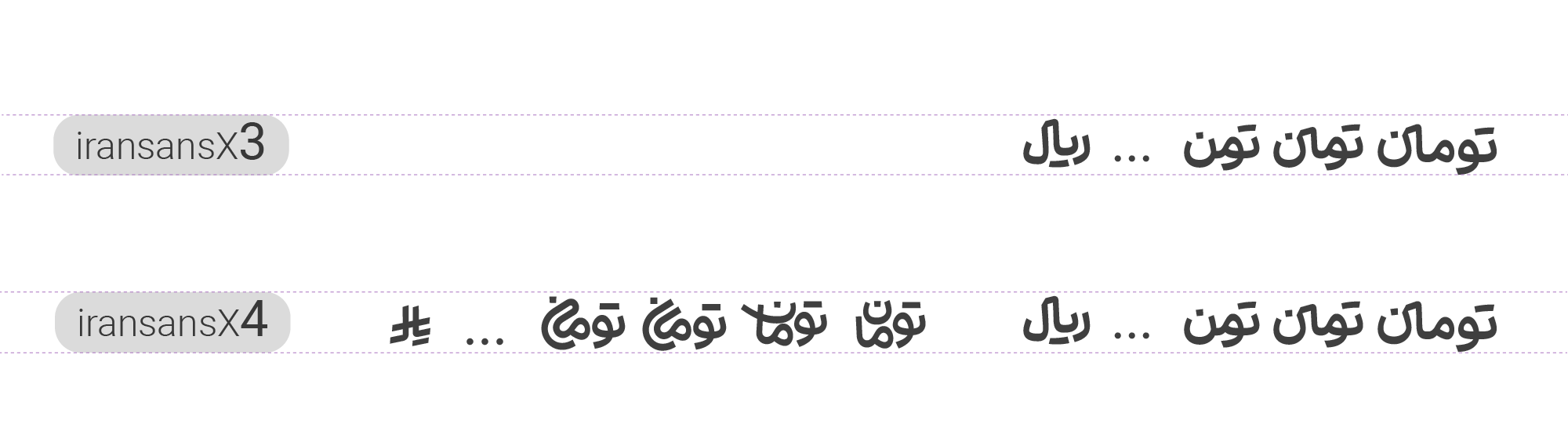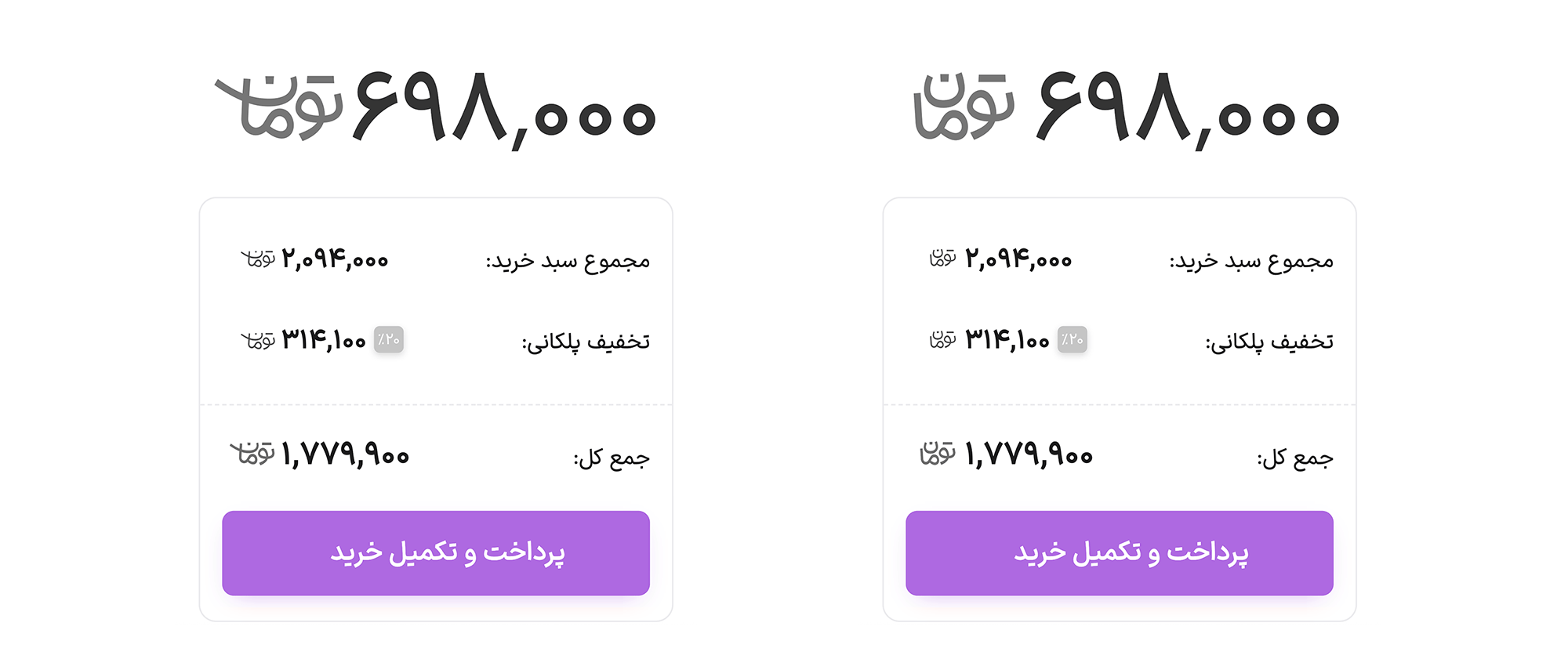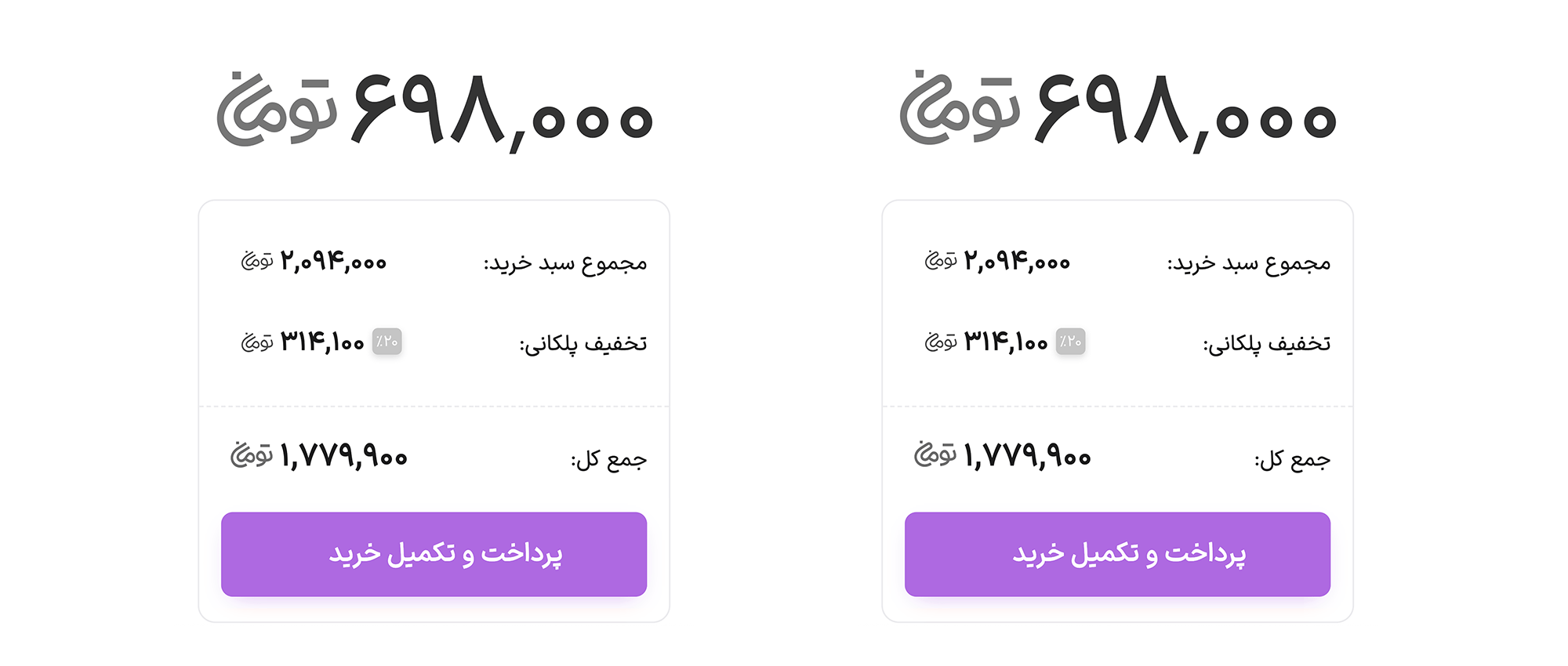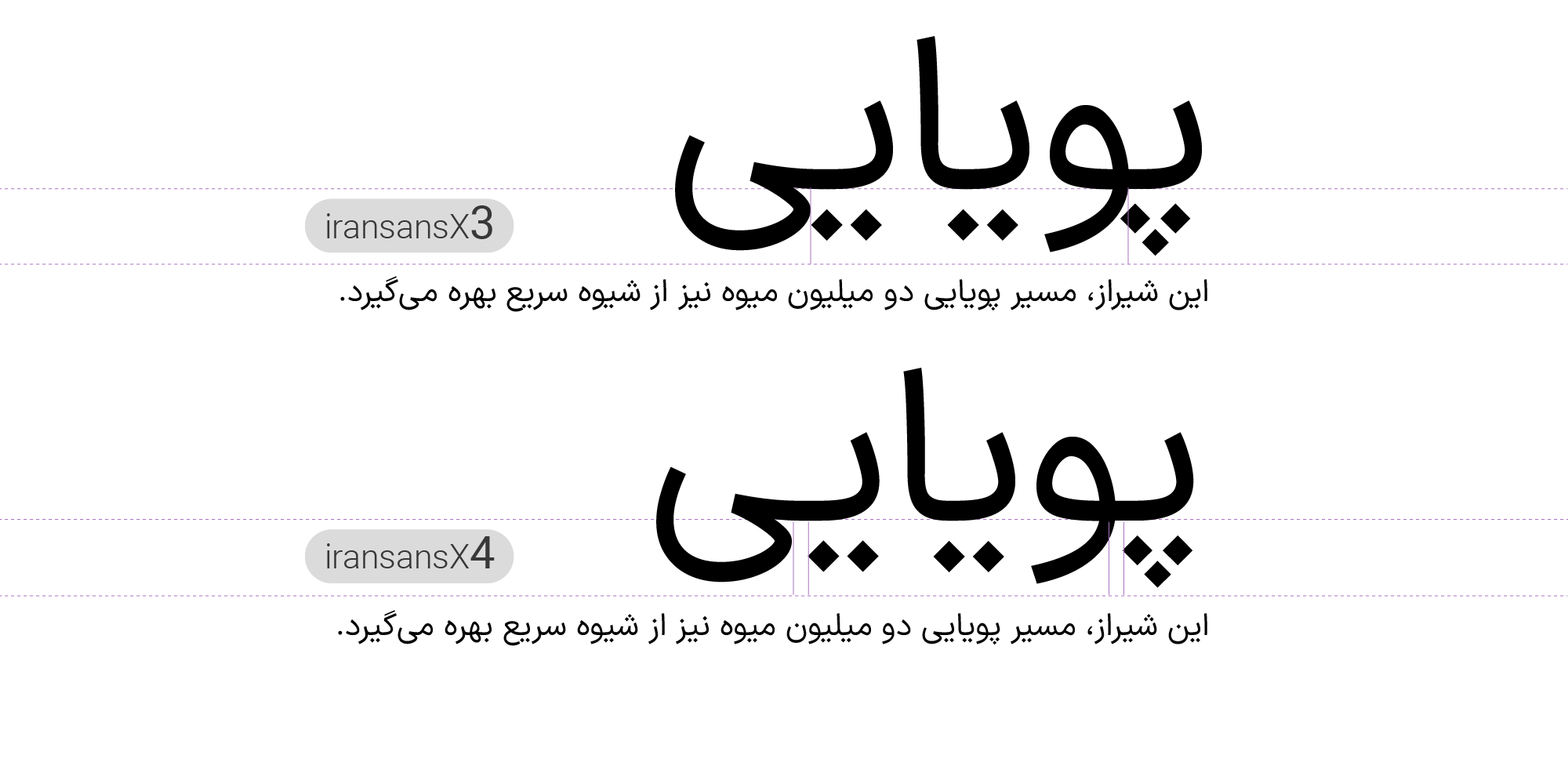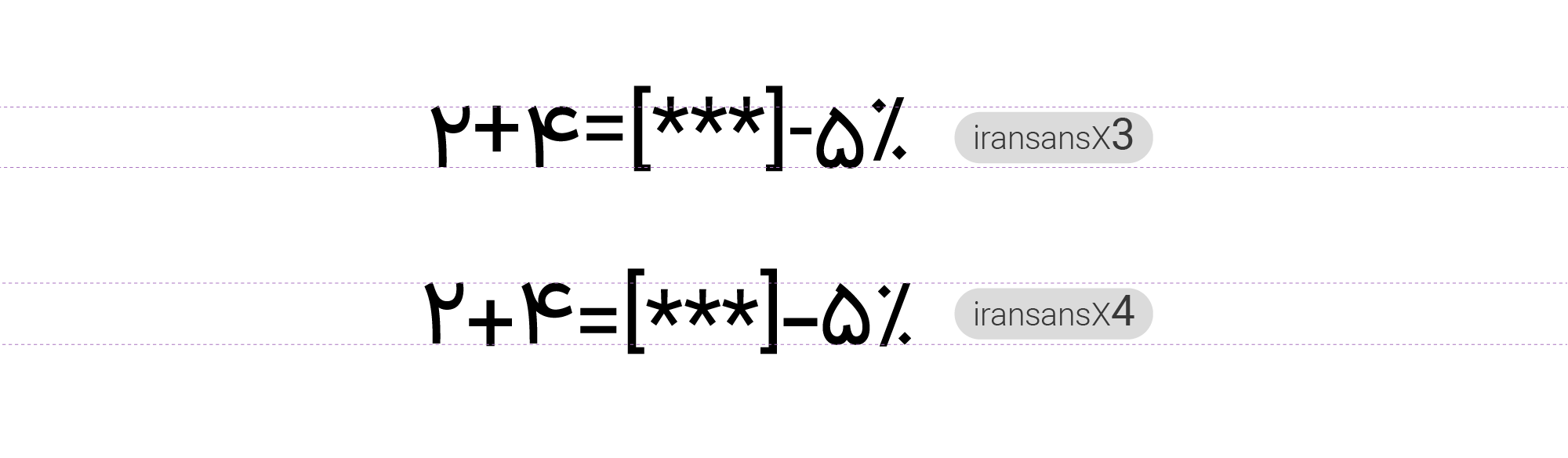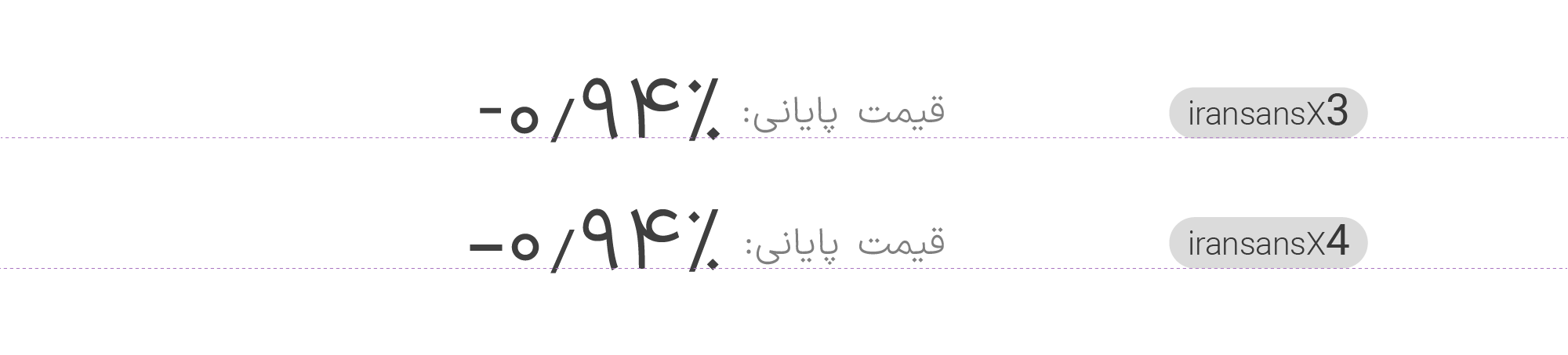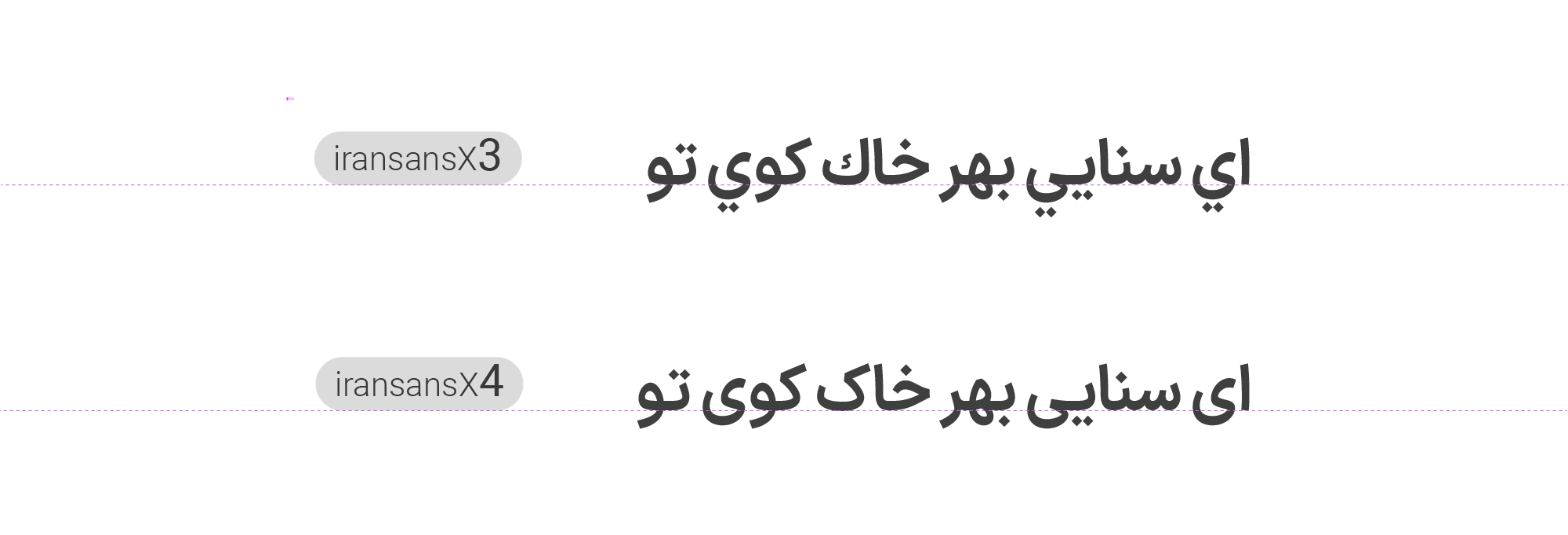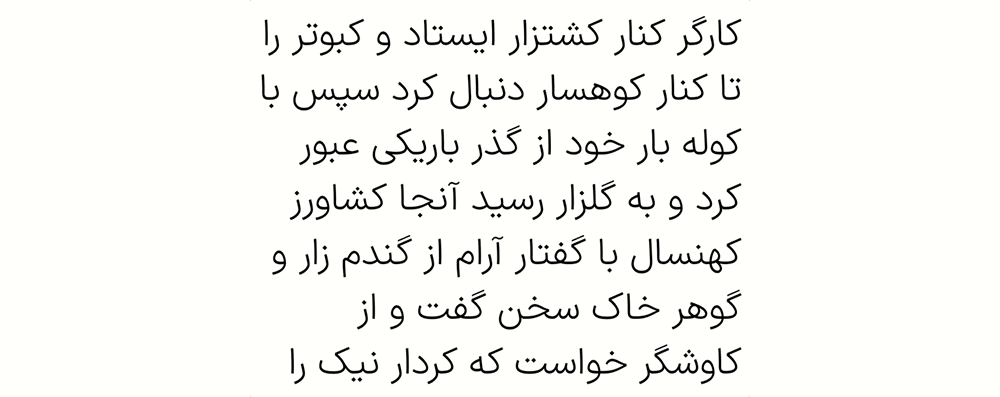
رفع مشکلات گزارش شده و اضافه شدن گلیفهای تومان در IRANSansX4
در نسخه جدید فونت ایرانسنس مشکلات تخصصی و ظریفی رفع شده است که کاربران حرفهای آن را گزارش کردهاند.
و امکاناتی اضافه شده است که در ادامه میبینید:
۱- اضافه شدن ۴ گلیف جدید برای تومان
۲- رفع مشکل عدم جانشینی درست نقطهها در مرورگر وب
۳- اکنون تراز عمودی علایم نیز متناسب با اعداد تغییر میکند
۴- اصلاح تراز علامت منفی
۵- فارسی شدن ي و ك عربی در نسخه FaNum
۶- رفع مشکل جابجایی متن هنگام انتخاب
۸- جایگزینها Stylistic Sets با توجه به کاربردشان نامگذاری شده اند.
۹- اکنون میتوانید امکان هم عرض شدن یا تغییر تراز عمودی را همزمان با فارسی کردن اعداد استفاده کنید.
۱۰- هم عرض شدن اعداد با فعال کردن Tabular هم امکان پذیر است.
۱۱- حالت جایگزین حروف (ک گ ه ی) از طریق Stylistic Sets نیز در دسترس است.